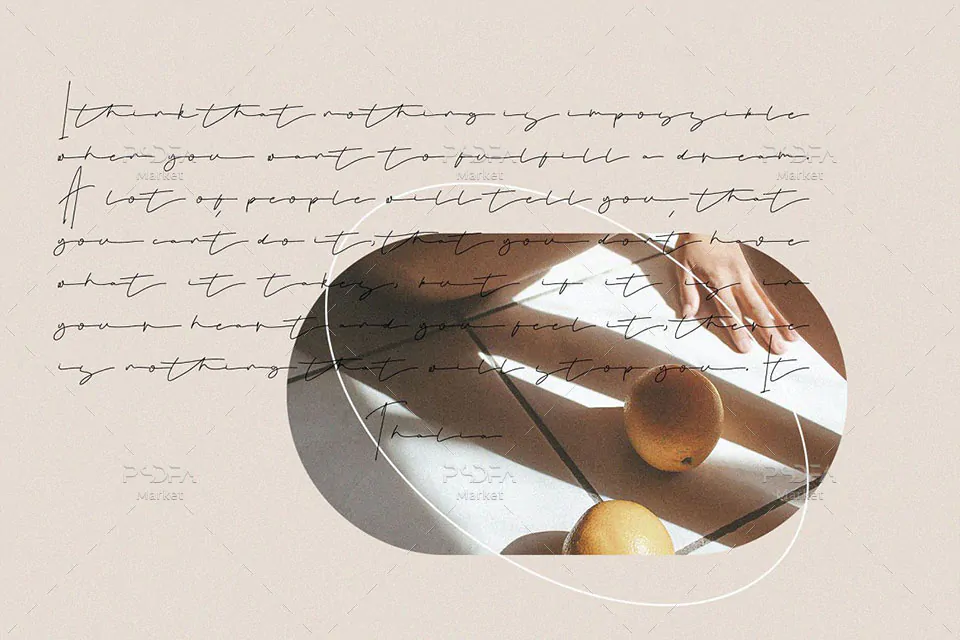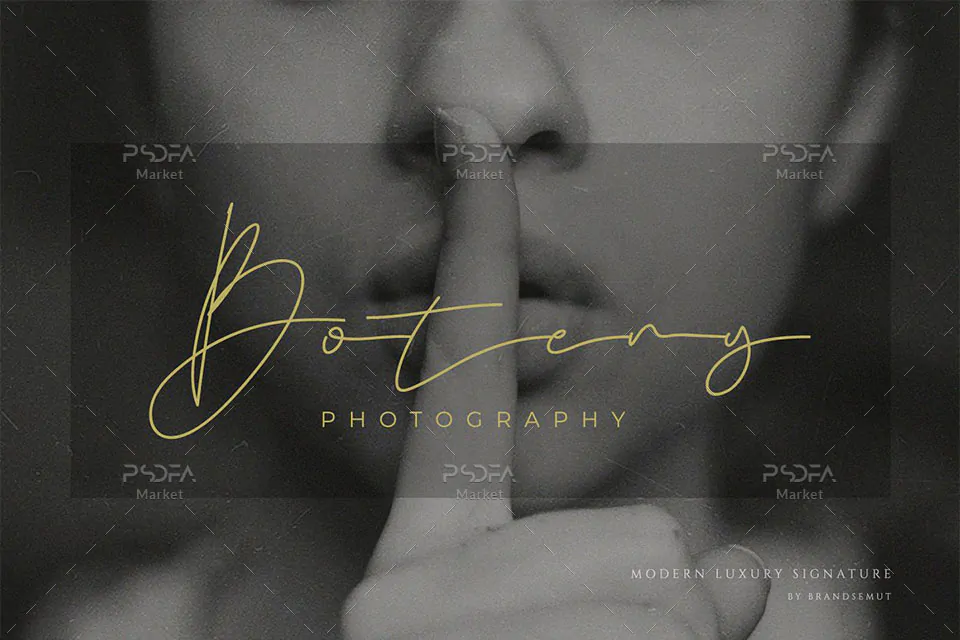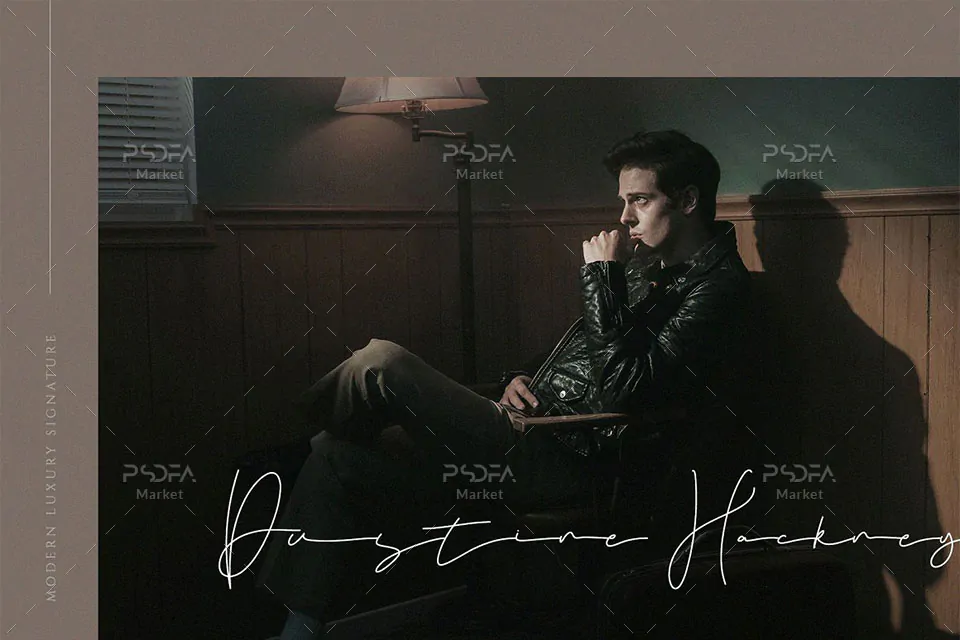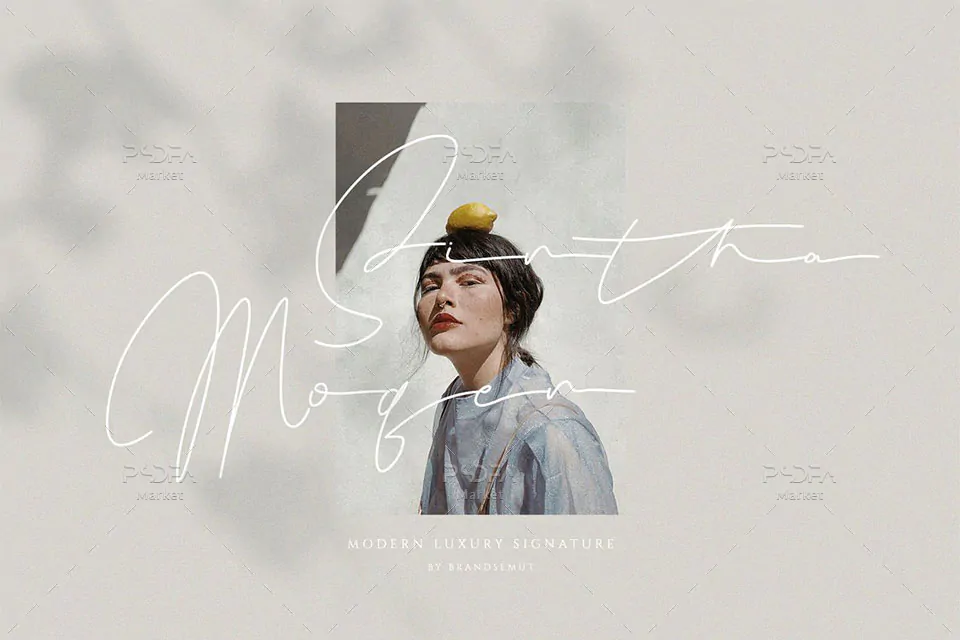
فونت انگلیسی دستنویس و امضایی شیک و زیبا Sintha Moqen
فونت انگلیسی دستنویس و امضایی Sintha Moqen
فونت انگلیسی دستنویس و امضایی شیک و زیبا Sintha Moqen یک قلم زیبای سرهمی دستنویس است که مناسب جهت استفاده در طرح و پروژههای گرافیکی مختلف به خصوص طراحی انواع کارت تبریک و کارت عروسی میباشد. این فونت زیبا در قالب 3 فایل OTF, TTF, WOFF در فایل محصول قرار دارد که با نصب یکی از دو فرمت ttf یا otf در پوشه فونتهای سیستم میتوانید از این فونت انگلیسی در تمام نرم افزارهای گرافیکی و تایپ متون همچون فتوشاپ، افتر افکت، پریمیر، ورد، پاورپوینت و … استفاده کنید.
فونت Sintha Moqen در وزن معمولی (Regular) طراحی شده است که میتوانید از آن در طراحی انواع کارت تبریک، کارت پستال، کارت ویزیت، کارت عروسی، کاور آلبوم موزیک، طراحی انواع بنر، پوستر، تراکت، تقویم و دیگر طرحهای گرافیکی استفاده کنید. از نسخه وب این فونت نیز می توان در طراحی صفحات وب استفاده نمود.
- کیفیت بالای قلم